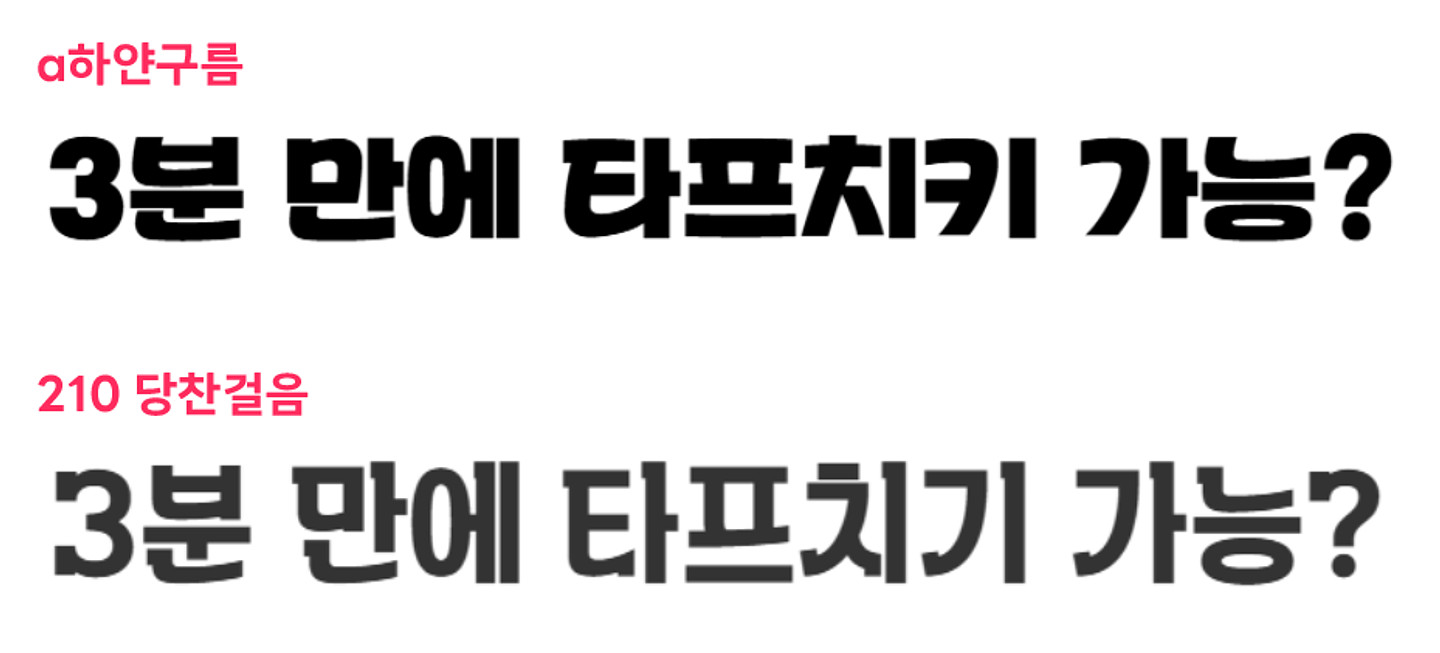
a하얀구름
a하얀구름 이 폰트랑 210 당찬걸음 자음 꺽인 부분이랑 합쳐서 타이포 작업한거 같아요!! a하얀구름 - https://www.asiafont.com/asfont/m_view.php?ps_db=sample&ps_boid=246 / 210 당찬걸음(유료) - https://www.sandollcloud.com/font/21767/210-Dangchangeoreum